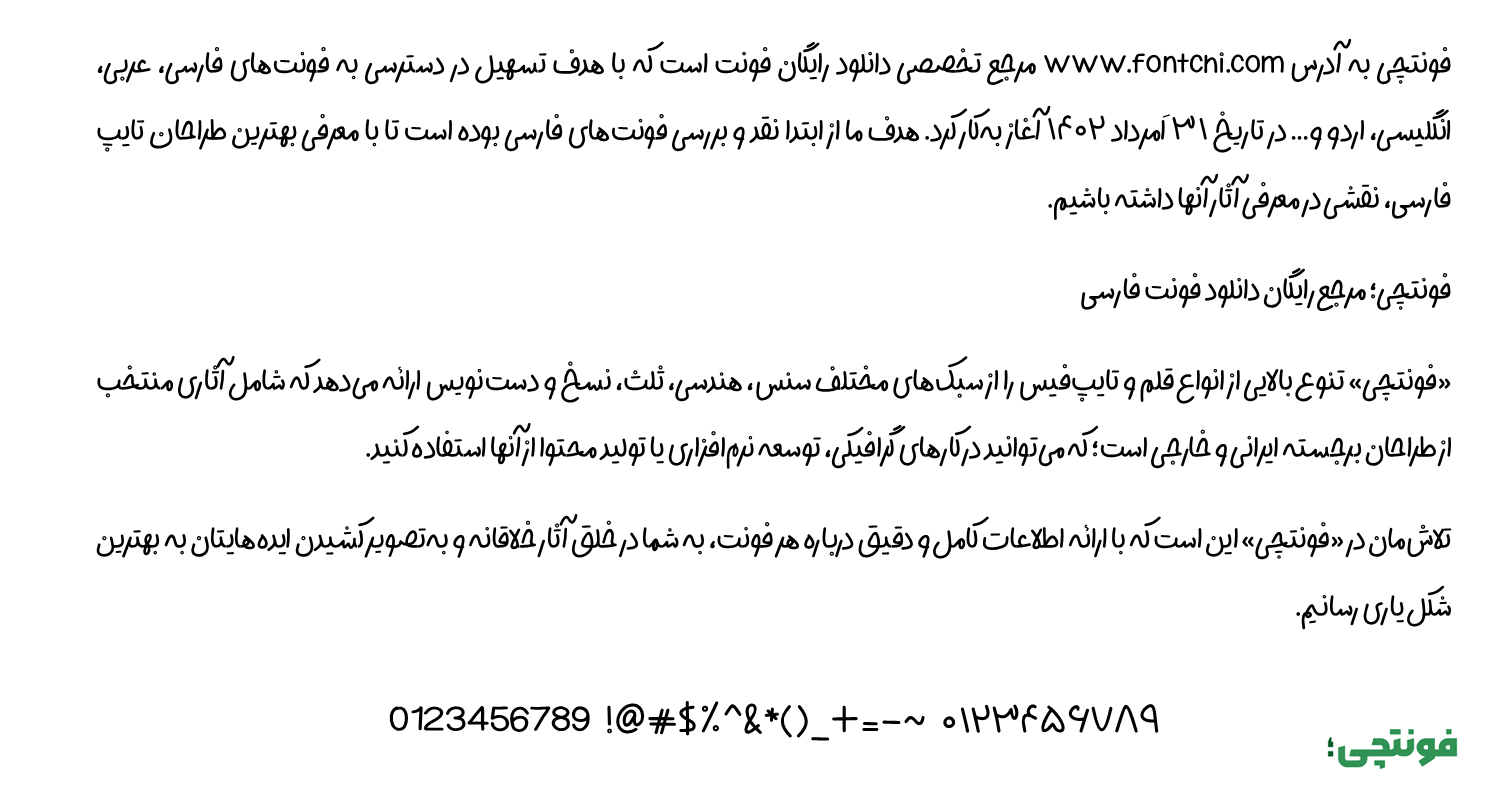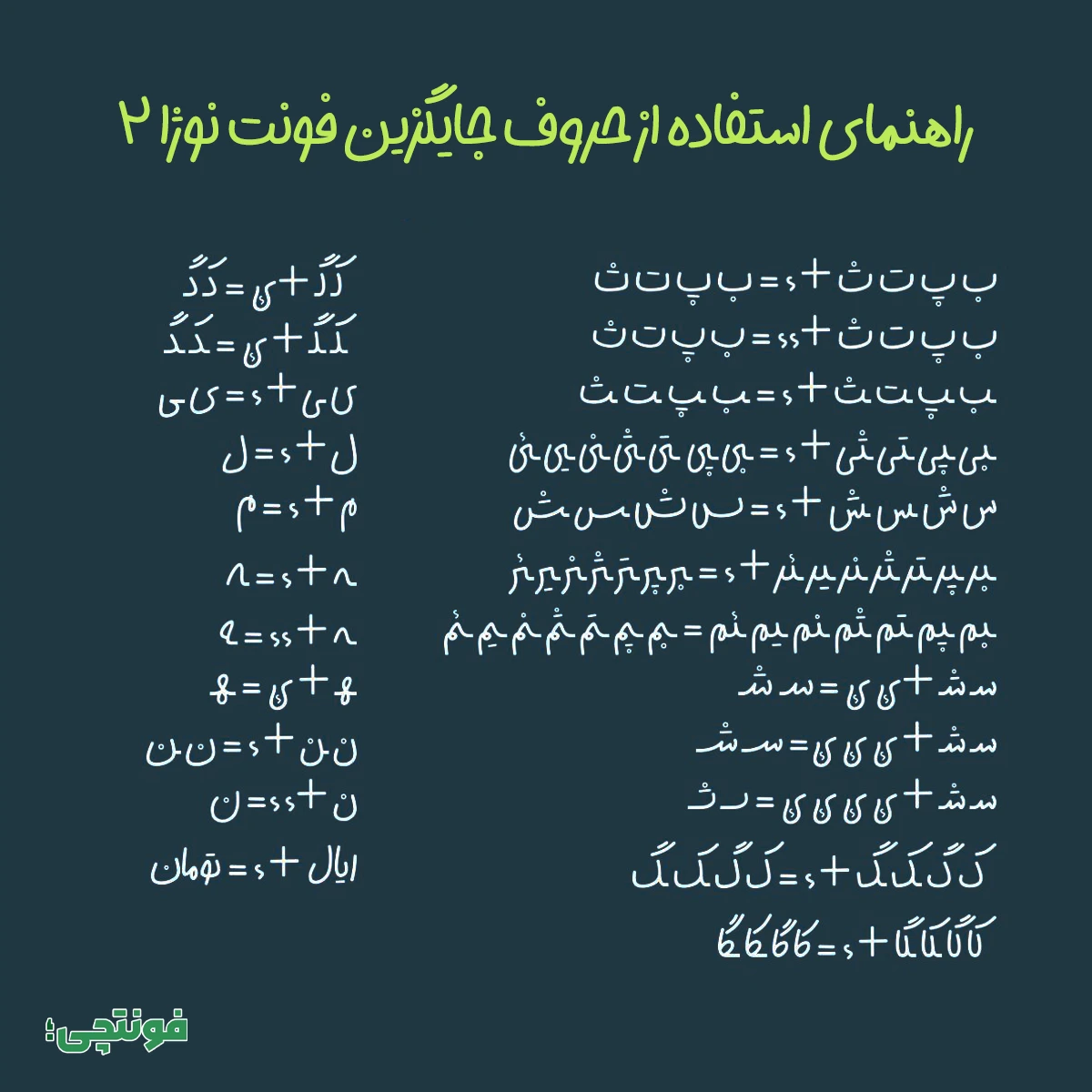
فونت دیجی نوژا ۲ (Digi Nozha۲)
فونت دیجی نوژا ۲ یا نوژا ۲ (به انگلیسی: Digi Nozha2) نسخه جدیدتر فونت دیجی نوژا دست نویس است که با ظاهری ضخیمتر و پشتیبانی از حروف جایگزین متنوع عرضه شده است. از این فونت فانتزی میتوانید در کارهای تبلیغاتی، متون کوتاه و عناوینی که نیاز به فونت نمایشی دارید استفاده کنید.
این فونت توسط مهدی برقگیر و با الهام از دستخط بهنوش آذری طراحی شده است که دارای ظاهری صمیمی، پویا، بازیگوش و جوان است. در ادامه با نقد و بررسی این فونت همراه ما باشید.
فونت دیجی نوژا ۲ محدود به زبان فارسی نیست. از این فونت فارسی رایگان میتوانید برای زبانهای کردی، عربی و انگلیسی نیز استفاده کنید. تنوع زبانی این فونت بهخصوص برای زبان فارسی که عبارات و اصطلاحات مختلفی را از سایر زبانها وام گرفته، برای متون ترکیبی عالی است.
در نسخه قبلی این فونت شاهد ظاهر معمولی و با ضخامت کمتر بودیم. اما در نسخه ۲ فونت نوژا علاوه بر افزوده شدن ضخامت بیشتر، ارتفاع حروف نیز کمتر شده که فونت را برای استفاده در عناوین نمایشی مناسبتر کرده است. همچنین تنوع بسیار بالایی از حروف و ترکیبات جایگزین به آن افزوده شده که ظاهر آن را فانتزی میکند.
از جمله کاربردهای فونت دیجی نوژا ۲ میتوان به موارد زیر اشاره کرد:
- عکس نوشتهها در شبکههای اجتماعی.
- عناوین تبلیغاتی با هدف قرار دادن احساس مخاطب.
- استفاده در بستهبندی و عنوان محصولات در حوزه کودک و نوجوان.
- مناسب برای عناوین و جلد کتاب یا استفاده برای مجلات و کتابهای مصور.
در طراحی حروف این فونت از کرنینگ متعادل و حرفهای استفاده شده تا در زبانهای مختلف، علائم نگارشی، اعراب و کاراکترهای تزئینی در جایگاه مناسب خود قرار گیرند. همچنین فواصل حروف نسبت به نسخه قبلی اصلاحاتی داشته است.
ترکیبات و حروف جایگزین فونت نوژا ۲
حروف جایگزین در فونت نوژا ۲ نقطه عطف این قلم نسبت به نسخه قبلی و همچنین تایپفیسهای دیگر ارائه شده توسط طراح است. با افزودن کاراکترهای خاصی که در تصویر زیر مشخص شده است، در میانه یا انتهای حروف و ترکیبات مختلف، میتوانید عبارات را با ظاهر متفاوت تایپ کنید.
علاوه بر ترکیبات جایگزین، امکان تایپ «تومان» به شکل متفاوت با استفاده از کاراکتر ترکیبی «ریال + ء» نیز فراهم است که آن را برای عناوین تبلیغاتی که قابلیت درج قیمت دارند مناسب میکند.